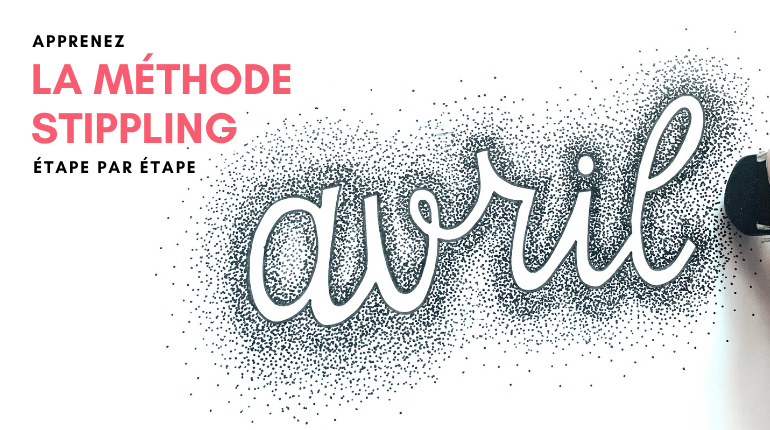
Apprenez la méthode du stippling pour embellir votre lettering
Aujourd’hui je vous propose de vous attaquer à la méthode du stippling pour embellir vos compositions et vos lettrages ! J’espère que vous avez un peu de temps devant vous car cela nécessite beaucoup de patience et de temps (en ce moment ce n’est pas vraiment ce qui manque…)
Le « stippling » ou pointillé en français qu’est ce que s’est ? C’est la création d’un motif ou d’ombres à l’aide de petits points. Et quand on parle de petits points, c’est point par point… D’où la nécessité d’être patient ! Petite astuce, quand je réalise cette technique, je mets généralement un podcast en fond ou une série, je vous assure le temps passe plus vite 😉
Le matériel nécessaire
Etape par étape
- Dessinez le mot que vous souhaitez illustrer
Je vous conseille d’utiliser des lettres avec un vide à l’intérieur car si vous dessinez des lettres « bâtons » on risque de ne pas bien faire la différence entre la lettre et les points. Vous pouvez aussi utiliser la méthode de la fausse calligraphie pour réaliser cet effet.
- Ajoutez 3 contours autour du mots
Tracez un contour autour du mot en essayant d’avoir toujours la même distance/espace entre le mot et le contour. Ajoutez 2 autres contours en les espaçant de plus en plus.
Méthode :
Plus vous êtes près du mot (1er contour) plus les points doivent être rapprochés et plus on s’éloigne du mot (3ème contour) plus les points doivent être éparpillés et loins les uns des autres
- Tracez le contour de votre mot au feutre fin
Cela vous permettra de mieux voir ou est votre mot et où doivent être les points. On effacera ces traits à la fin.
- Tenez votre feutre fin droit et appuyez sur la feuille pour faire des petits points très près les uns des autres (très concentrés) dans le premier contour. C’est l’étape qui prend le plus de temps car c’est là où il y a le plus de points !
- Une fois le 1er contour fini, commencez à faire des petits points sur le 2ème contour et cette fois-ci plus écartés. N’hésitez pas à revenir dessus après pour être sûr que le passage du 1er au 2ème contour n’est pas trop différent, il faut qu’il y ait comme un effet de fondu.
- Une fois le 2ème contour terminé, c’est le moment de s’attaquer au 3ème et dernier contour ! Cette fois-ci on cherche vraiment à éparpiller les points et à en faire le moins possible !
Laissez sécher 5/10 minutes et gommez les tracés. Et c’est dans la poche ☺️
Une autre méthode plus rapide
Ici, nous avons réalisé la méthode stippling à l’extérieur du mot pour créer un effet de halo et d’ombres. Seulement vous pouvez également créer et un effet de stippling à l’intérieur même des lettres.
Ici, j’ai repris exactement le même mot, dessiné de la même façon et j’ai appliqué la méthode stippling à l’intérieur du mot. Vous pouvez le faire partir du bas (comme sur l’exemple ci-dessus), du milieu ou du bas !